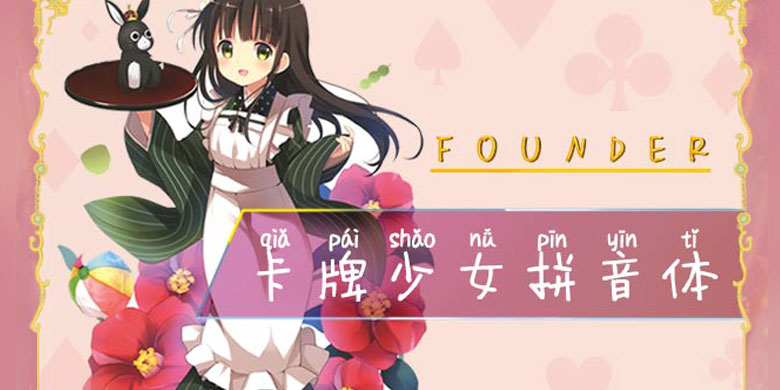
方正手迹-卡牌少女拼音体
方正手迹-卡牌少女拼音体,这款字体结构工整、笔画清晰,兼顾美观与易读性,适用于标题、正文、海报、包装、LOGO 等多种场景。字形优雅稳定,风格百搭耐看,适配日常排版与创意设计,让文字呈现更舒适、更具质感。方正手迹-卡牌少女拼音体一笔一画,皆是细节,以均衡的比例、流畅的线条打造舒适视觉体验,字形端正大气,风格简约现代。无论是商业设计、品牌宣传还是日常排版,都能轻松驾驭,让文字更有格调与力量。方正手迹-卡牌少女拼音体字体下载。
卡牌少女拼音体,字形打破常规,左低右高,整体向右上倾斜,活泼有趣,青春朝气,奋发向上。适用于少儿漫画类的书刊、品牌广告和产品包装设计,影视综艺用字,以及社交网络的个性化用字。